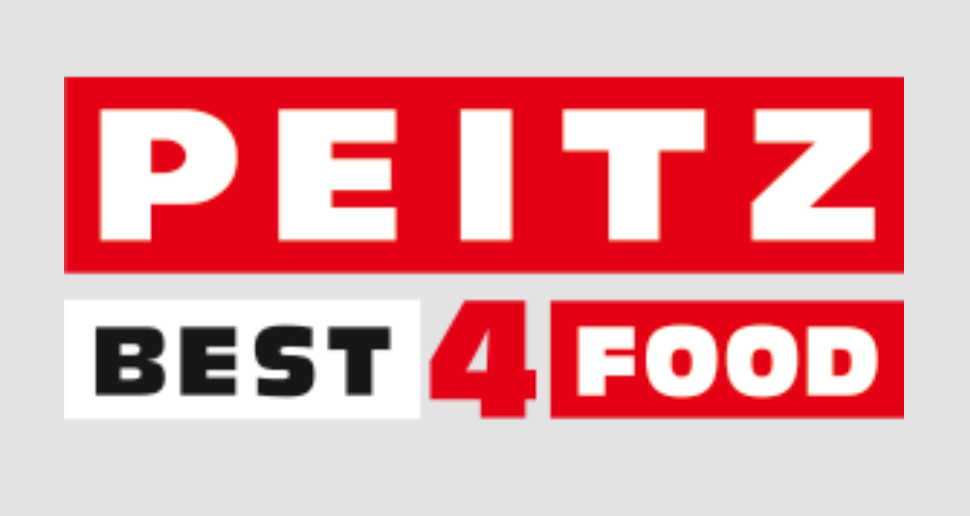
Suche Schrift dieses Firmenlogos (PEITZ)
ich suche die Schrift dieses Firmenlogos (PEITZ - Best 4 Food). Leider habe ich keine weiteren Informationen.
Ich hab mal eine Frutiger UltraBlack in 40% Schwarz darübergelegt … ist in Details abweichend, aber vielleicht nahe genug dran.